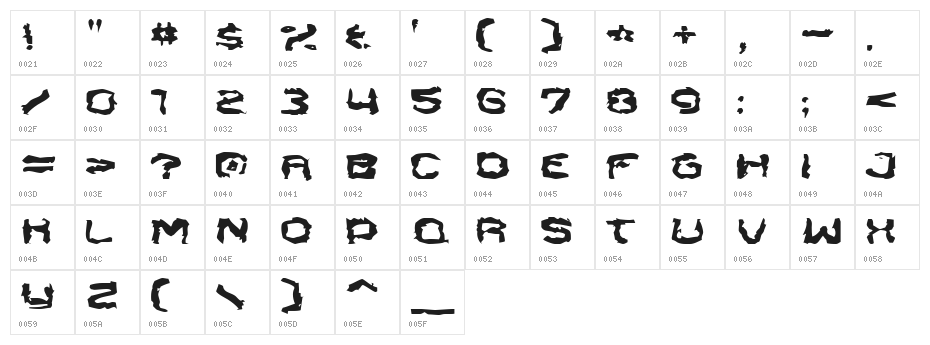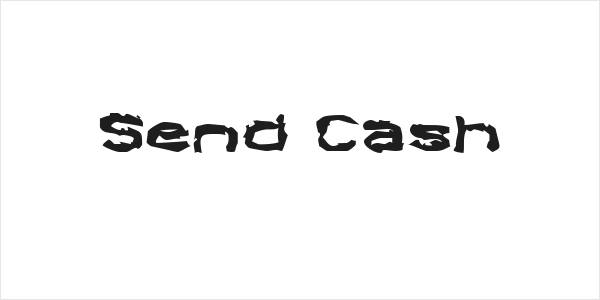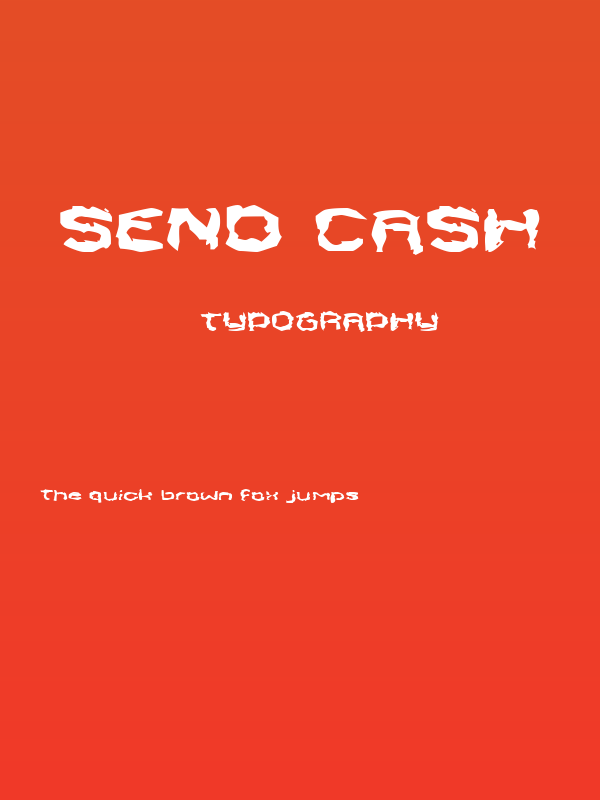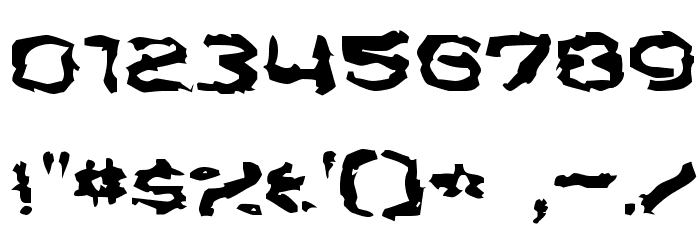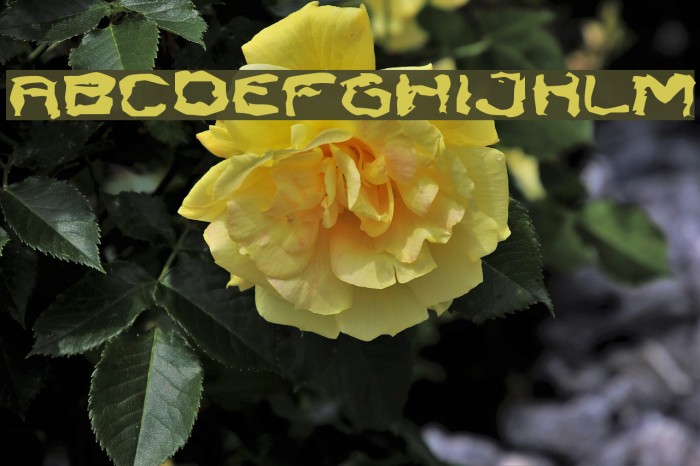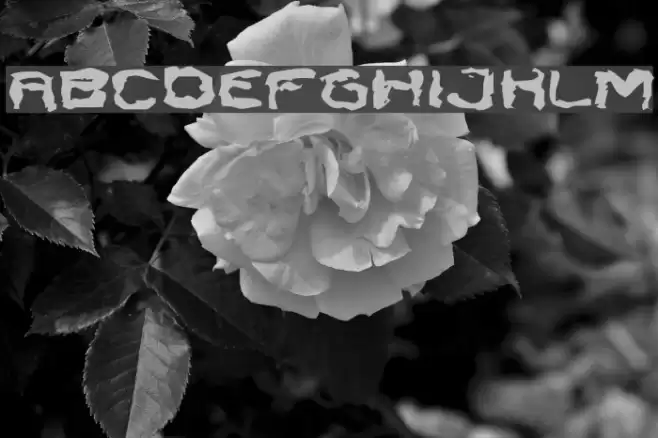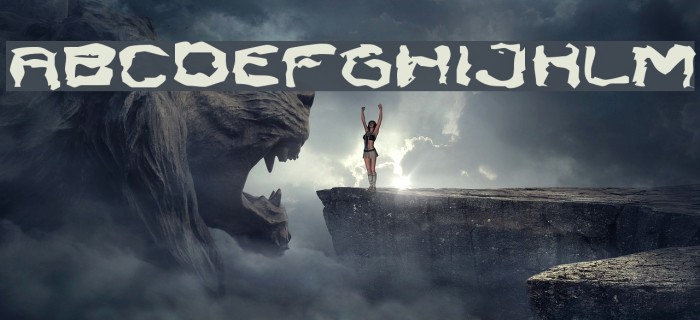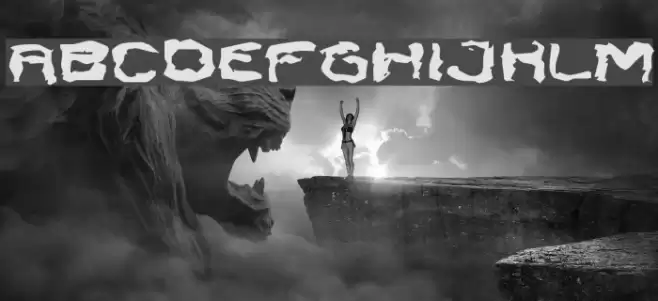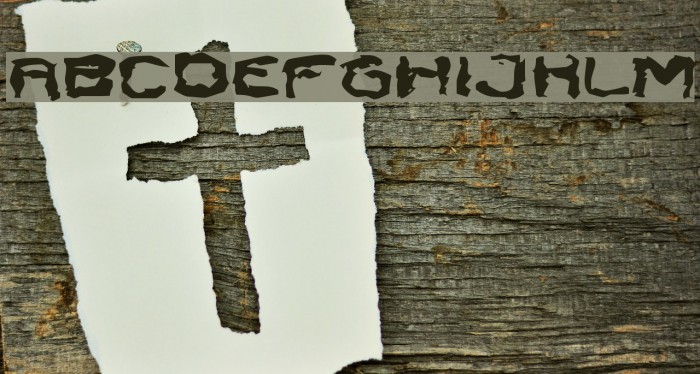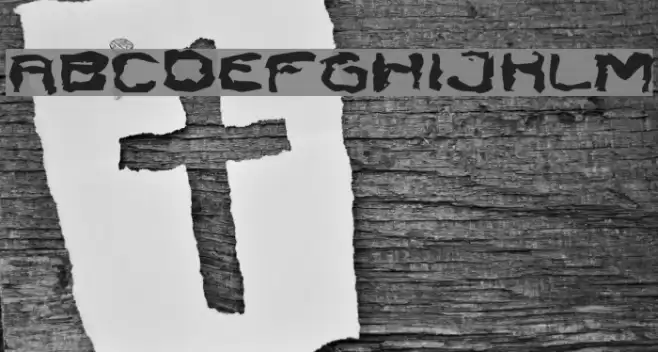
Send Cash Font
✎ Distorted Eroded
| Vorgeschlagene Projekte | Ideal for projects requiring a bold statement, such as posters, album covers, or branding for edgy or alternative products. |